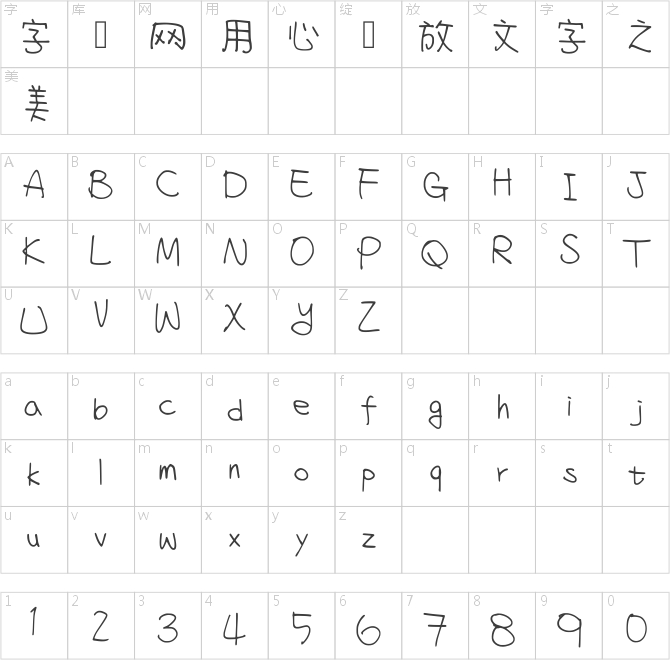
清松手寫(xiě)體6
游清松
清松手寫(xiě)體是游清松在稿紙上用原子筆手寫(xiě),透過(guò)“守寫(xiě)字”網(wǎng)站產(chǎn)生出初稿字型檔,再字體軟件制作加工而成的手寫(xiě)字型。
清松手寫(xiě)體手寫(xiě)字型,沒(méi)有一般電腦字型的生硬感,多了幾分手寫(xiě)般的自然感。不論是中文、英文、符號(hào)數(shù)字,適合在電腦屏幕上閱讀、排版、打印出來(lái)效果也很棒!
清松手寫(xiě)體6字體字庫(kù)是一款讓人賞心悅目、百看不厭的中文字體,適合各類(lèi)廣告和產(chǎn)品包裝設(shè)計(jì)應(yīng)用,字體大小7.12MB,格式為ttf字體,上傳用戶是余曉艷,作者/版權(quán)方為游清松